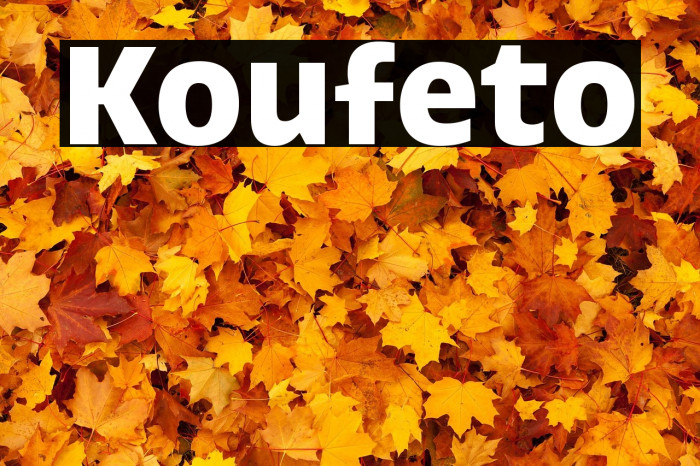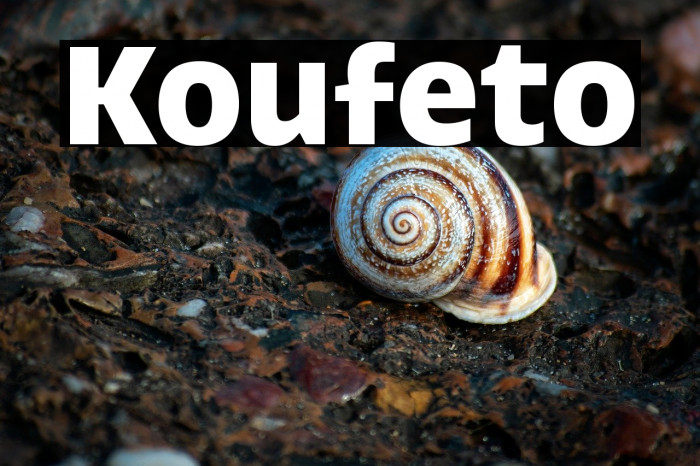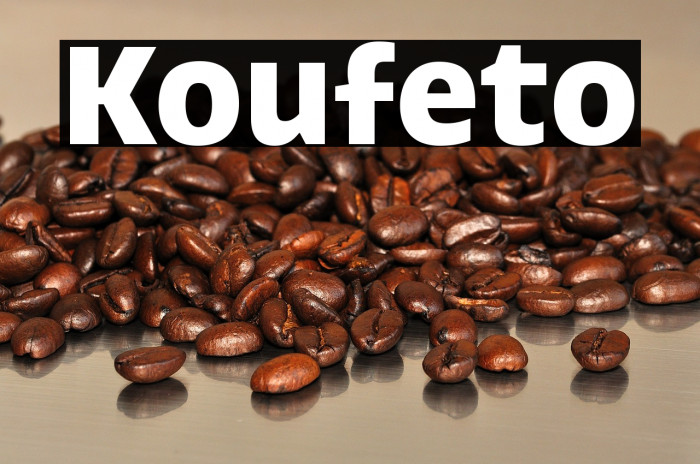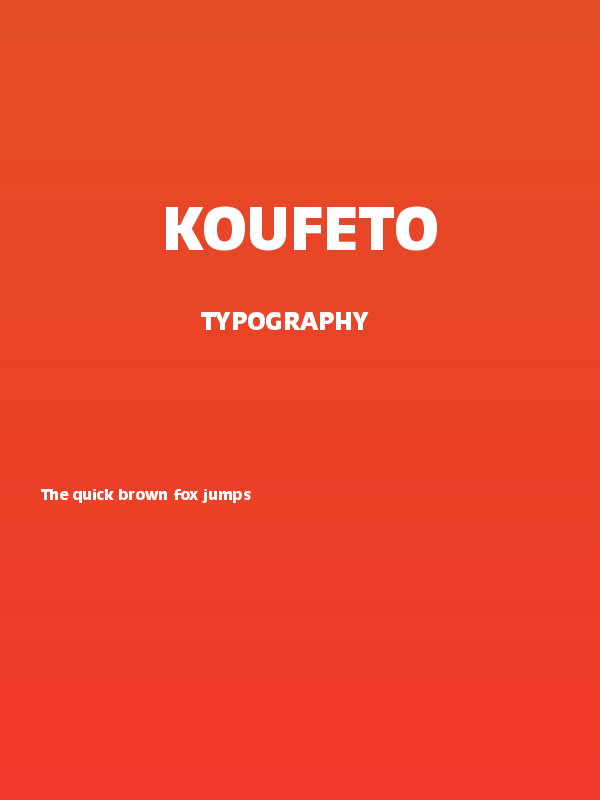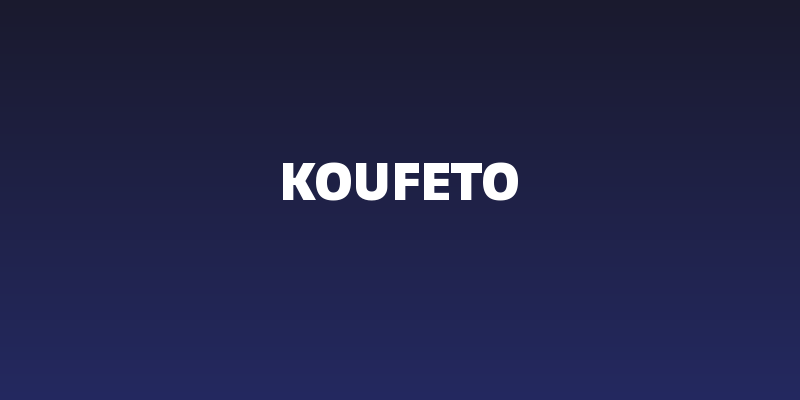
Koufeto Font
✎ Sans Serif
| Vorgeschlagene Projekte | Ideal for branding, advertising, headlines, and any project requiring a bold and modern typeface. |